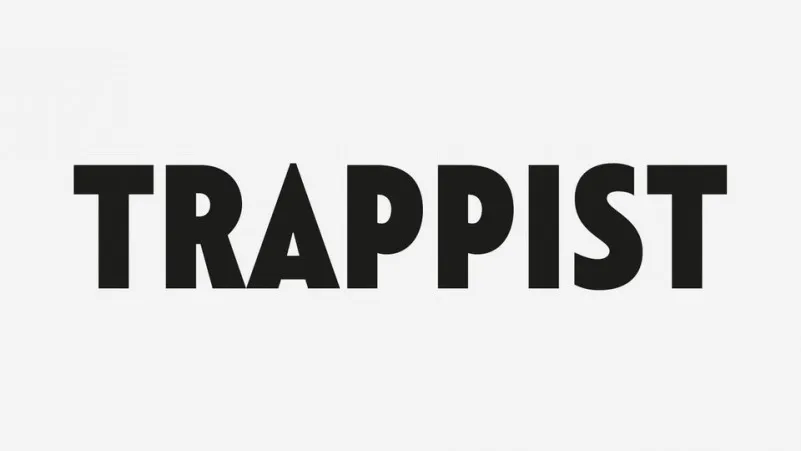
Através da Trappist Sans Serif Font, você encontra uma tipografia séria e emocional que se destaca na cena dos tipos modernos. Inspirada no movimento minimalista do século XX, essa fonte traz uma estrutura lógica e um equilíbrio óptico único. Ideal para aplicar em cartazes de filmes e headlines interessantes, esta fonte é perfeita para quem busca letras que expressam sua própria atitude. Com linhas puras e precisas, a Trappist Sans Serif Font representa um entrelaçamento entre geometria pura e equilíbrio óptico. Esta fonte é especialmente adequada para aplicação em logotipos, cartões de visita, citações, flyers, identidades corporativas, cabeçalhos de blogue ou até mesmo em ilustrações de citação. A Trappist Sans Serif Font oferece uma gama de possibilidades criativas que podem se adaptar a diferentes formatos e usos da comunicação visual.